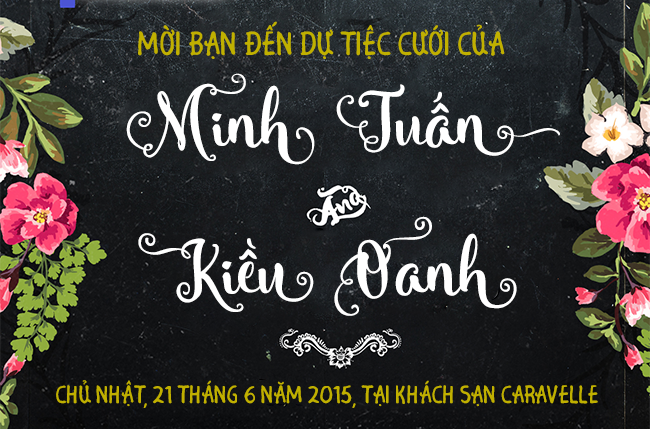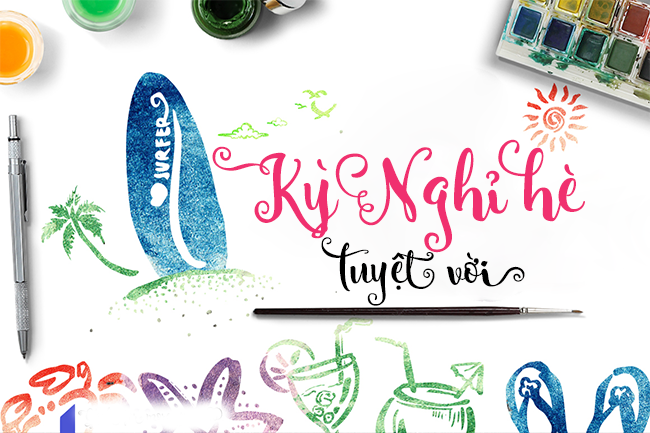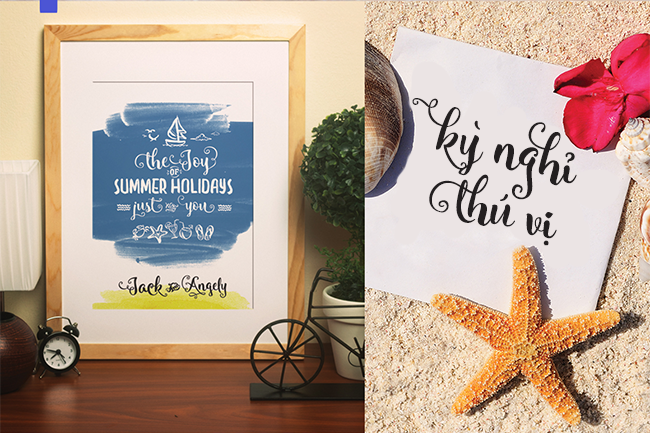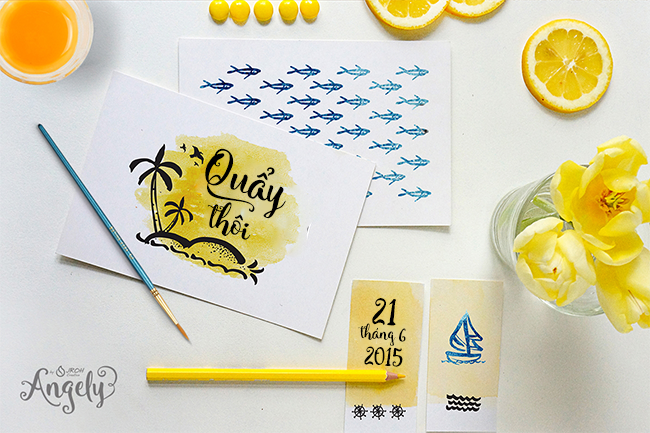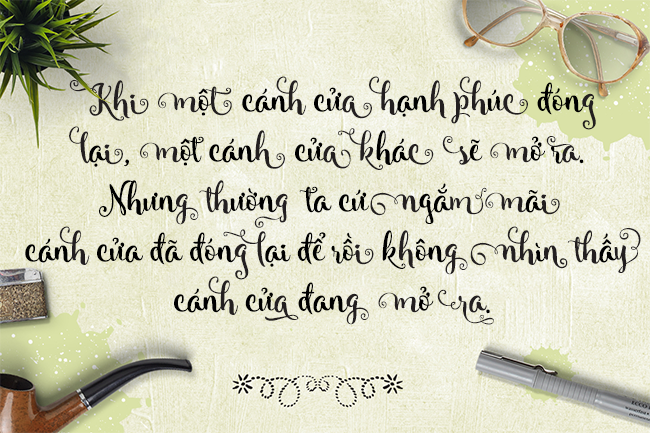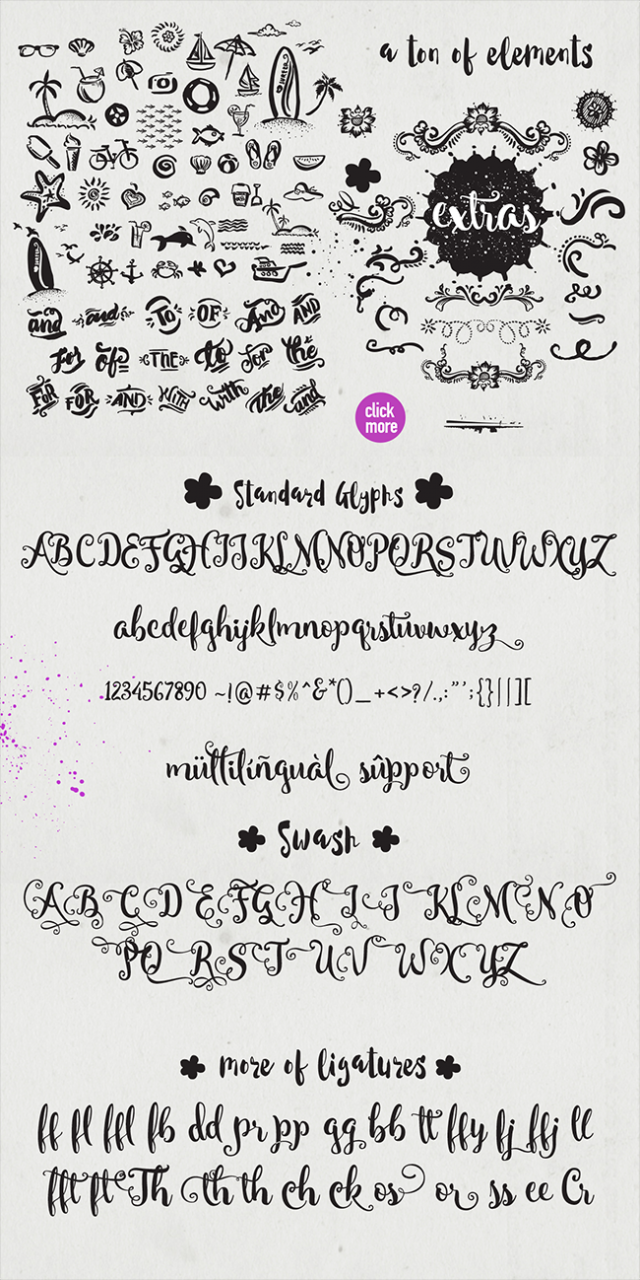
Giới thiệu Angely, một typeface lettering mới với rất nhiều yếu tố bonus. Phù hợp cho các dự án kỳ nghỉ hè, thiệp cưới, poster, câu trích dẫn, thiệp mời hoặc thiệp chúc mừng. Các tính năng OpenType bao gồm: standard ligatures, contextual alternates, swash, stylistic alternates.
Nhà thiết kế: @zamroni_agus
Nhà phát hành: Jroh Creative